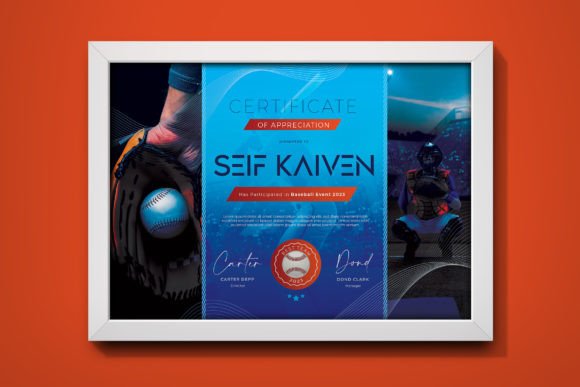
Baseball Certificate
Baseball Certificateのような高品質の素材をお探しの場合、このプレミアムパッケージはクリエイティブなプロジェクトに素晴らしい選択です。
精密に作られたBaseball Certificateは、クリーンなベクター、滑らかなタイポグラフィ、そして安心のための商用ライセンスを提供します。